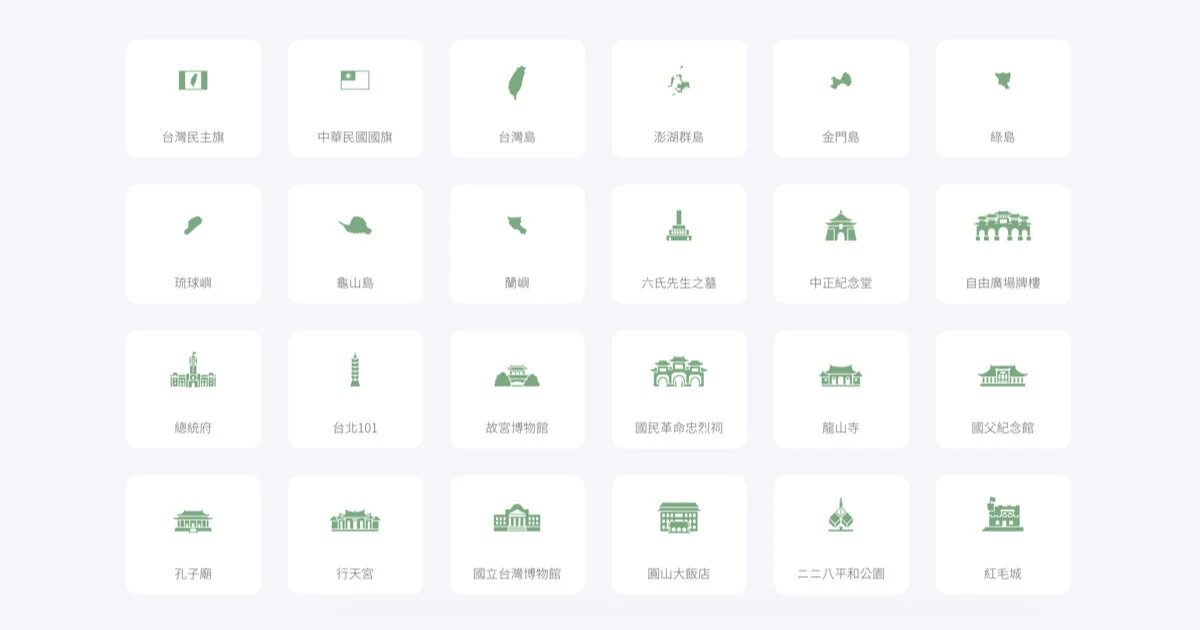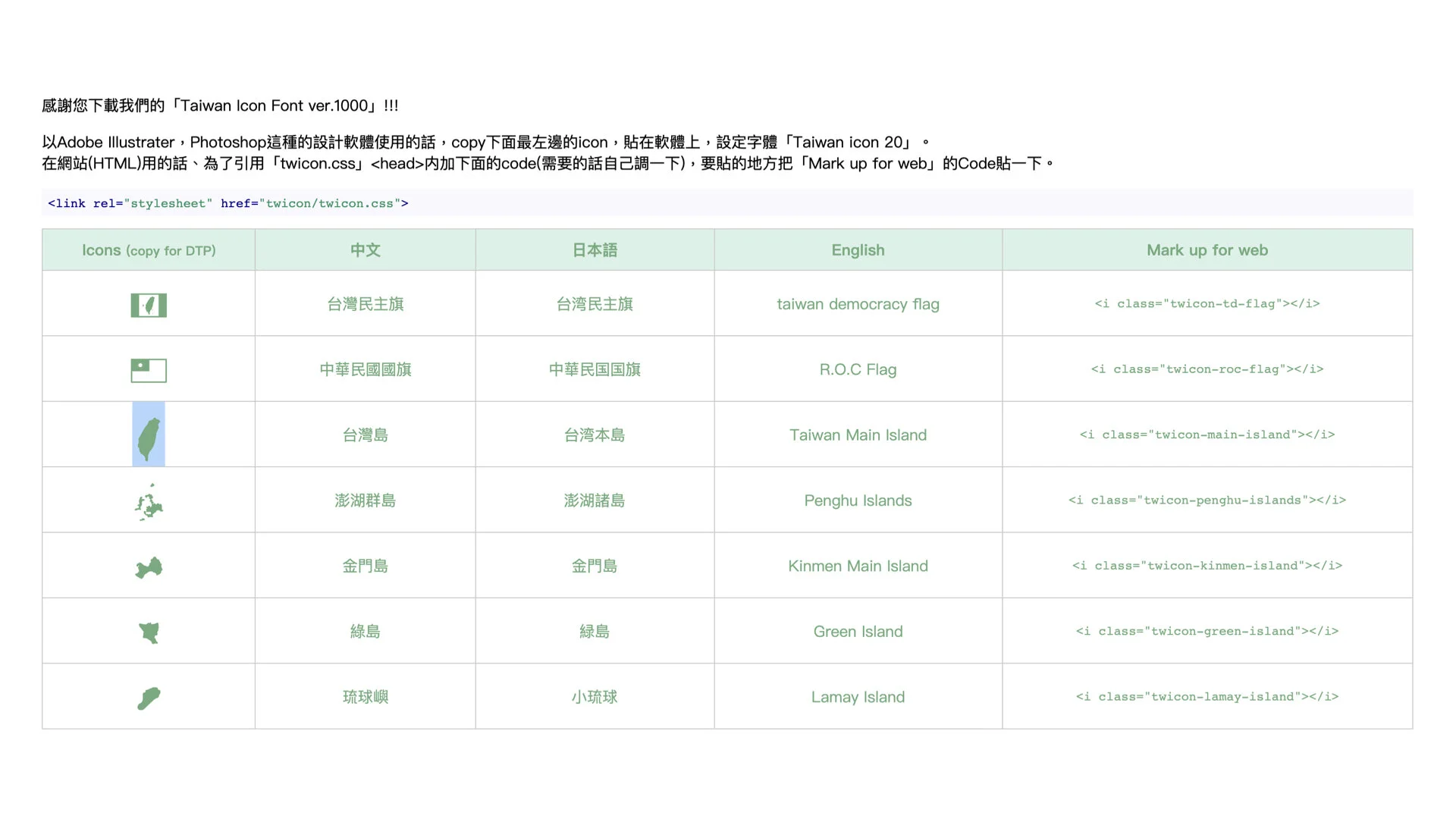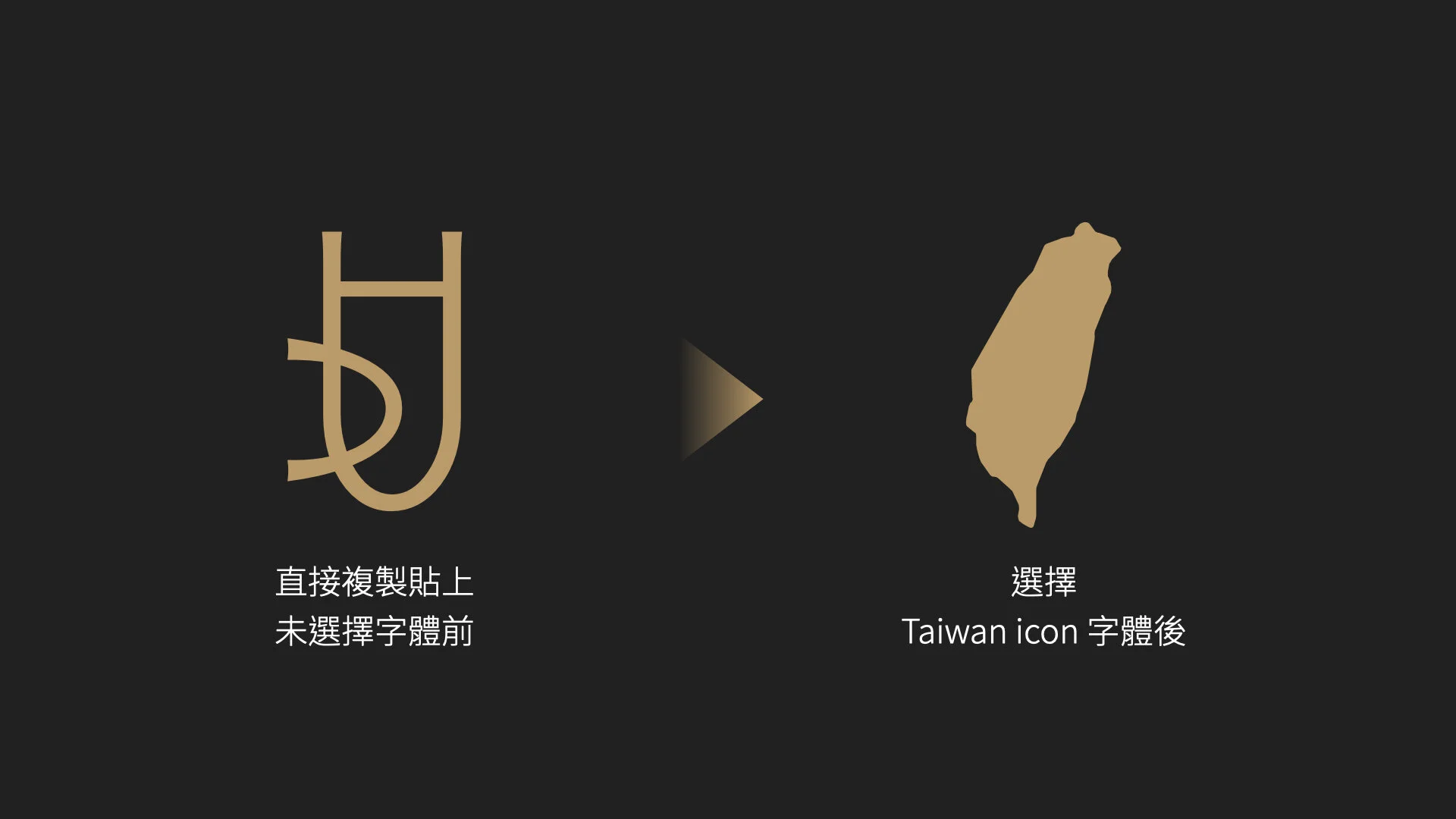
愛上一個地方最好的方式,就是為這個地方創作。
從 2019 年 6 月就開始住在台灣的日本設計師 Holoko,以及從英國來台定居的程式設計師 Rob,這兩位設計師共同打造了 100 個象徵台灣的特色圖標「Taiwan Icon Font」,總共分成地標、產品、交通與其他四大類別。
從台灣最南的屏東鵝鑾鼻燈塔、高雄蓮池潭龍虎塔、台中國家歌劇院到台北 101,還有聞名世界的手搖飲珍珠奶茶、婆婆媽媽上市場最愛的茄芷袋、廟宇的筊、藍白拖、大同電鍋等,零零總總共 100 個代表台灣在地風情的圖標,都在「Taiwan Icon Font」中完整收錄。
Holoko 和 Rob 為了讓更多人認識台灣,在圖標的設計中大量使用民生用品和著名景點地標,希望能讓外國人透過圖標就能對台灣更熟悉,並進一步來台灣旅遊。
了解「Taiwan Icon Font」台灣圖標的基本使用方式後,接下來,我們回到商業簡報的使用情境。在商業簡報中,圖標的使用原則有兩個,分別是「風格保持一致性」和「圖標加文字說明」。
圖標化的第一個使用原則:風格保持一致性
在商業簡報中,如果出現過多種不同風格的圖片、圖標、色彩或文字,都會讓簡報頁面看起來凌亂、不夠專業,比較好的做法是「有意識的使用圖片、圖標、色彩、文字」,在圖像元素的選擇上,盡可能選擇同一種風格,例如:統一使用單一色調、外國 / 亞洲人像等,這樣才會讓簡報看起來保持一致性。同樣的,若要使用「Taiwan Icon Font」台灣圖標在簡報中,也盡可能的使用此系列的圖標。
圖標化的第二個使用原則:圖標加文字說明
在「Taiwan Icon Font」台灣圖標中,因為非常的在地化,所以只有對台灣有一定程度熟悉的人能有辦法理解圖標含義。不過在商業簡報的情境中,理想的作法是為您的圖標加上文字輔助說明,來幫助聽眾理解您的簡報內容。因為面對沒有說明文字的圖標,聽眾往往會有自己的解讀,不同的解讀會提高溝通的成本。所以,要讓簡報有效率的達成目標,其中一個關鍵要素就是:聽眾可以輕易理解。
最後,回顧 Holoko 和 Rob 第一版的創作初衷,才知道原來兩位設計師是受到中國限制陸客來台旅遊所啟發,他們希望透過免費的台灣特色圖標,讓世界看見台灣。兩位設計師也在部落格中提到,在 2011 年日本東北大震災時,台灣的慷慨捐助讓兩國之間的關係更緊密,也是台日之間最美好的情誼。